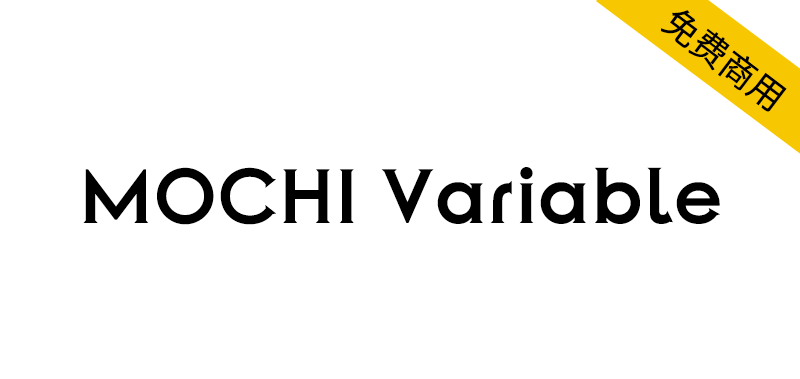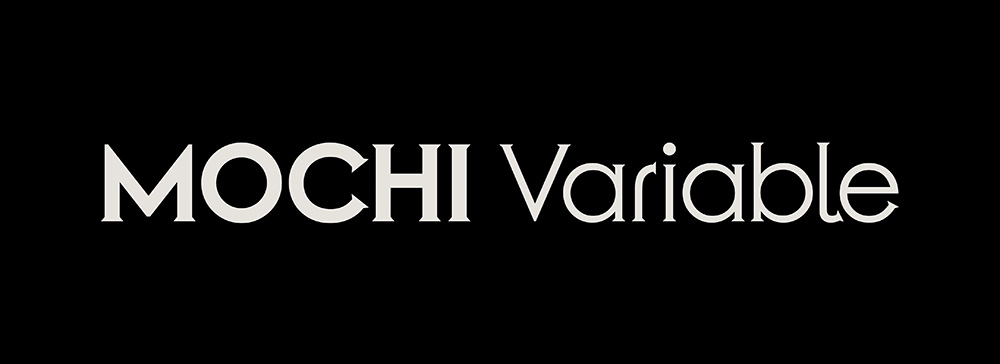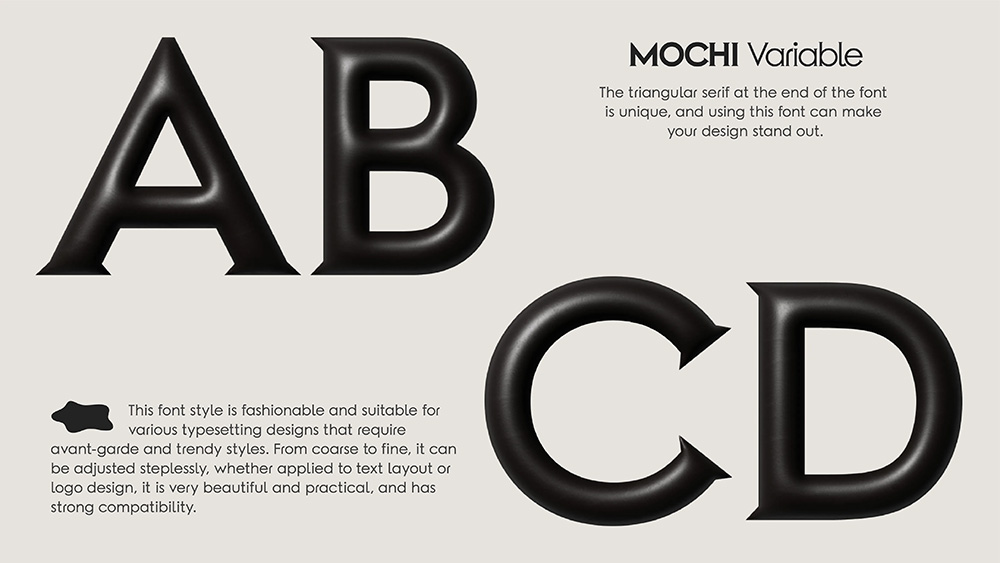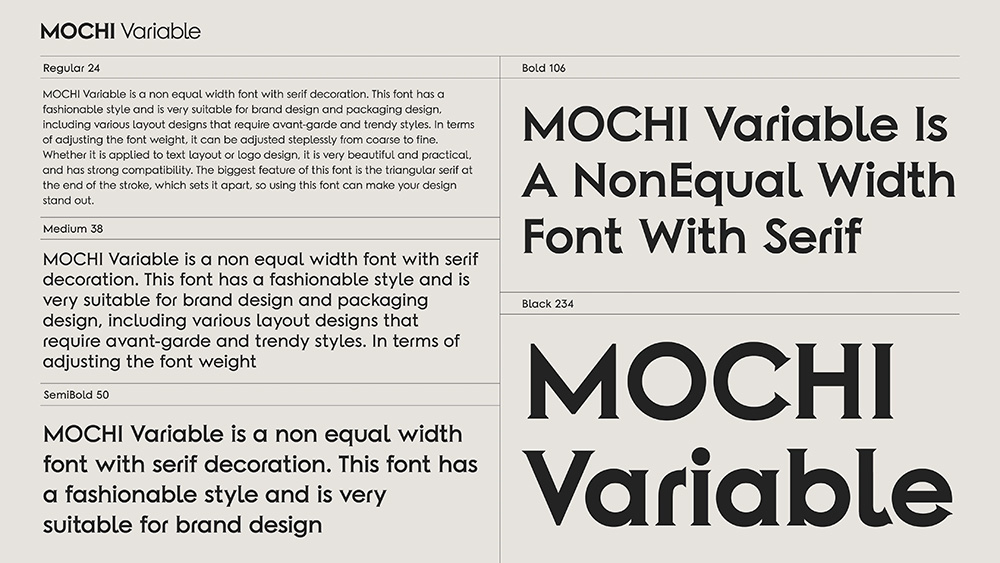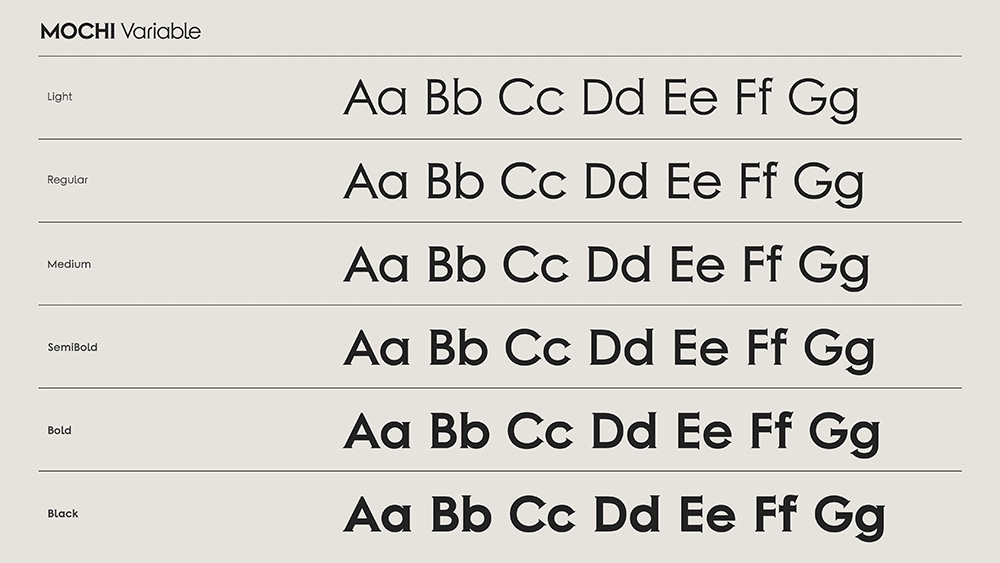
【MOCHI Variable】即前卫又复古庄重的可变英文字体
MOCHI Variable的风格来源于Copperplate Gothic,笔画末端有微小的衬线装饰,该风格字型已经有百年历史,即前卫,又能保留复古庄重的氛围感,这是一个在衬线与无衬线之间的好选择。而MOCHI Variable的骨架参考了Century Gothic,因为个人比较喜欢这样的非等宽的西文,但是在粗体上和小写字母还是做了很大的结构调整。由于是个人初习Glyphs的作品,有许多不足与缺漏之处,还请各位设计师朋友多多谅解。